1、字语可蓝体
字语可蓝体这款字体运笔舒展飘逸,部件排列别具一格,韵味缠绵,恍如初见心动一刻,呼之欲出的雀跃感受。适用于文艺类的书刊、品牌广告和产品包装设计,以及社交网络的个性化用字。
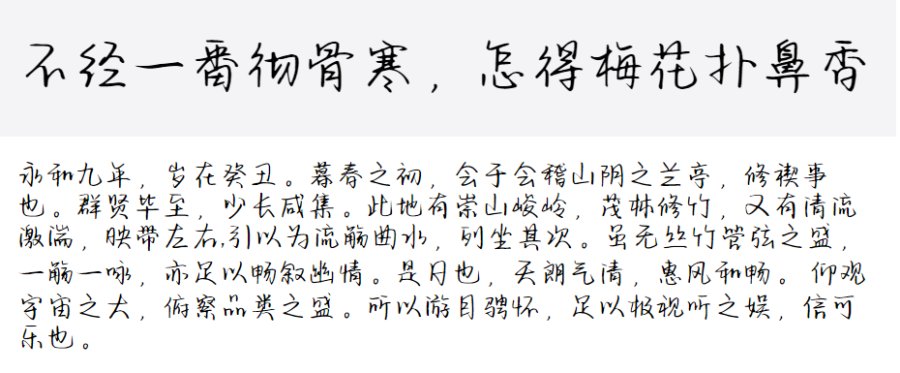
2、字语素笺体
字语素笺体这款字体笔画质朴,结构简单个性,转折处方中带圆,趣味十足。适用于动漫用字、少儿类书刊、品牌广告和产品包装设计,以及社交网络的个性化用字。
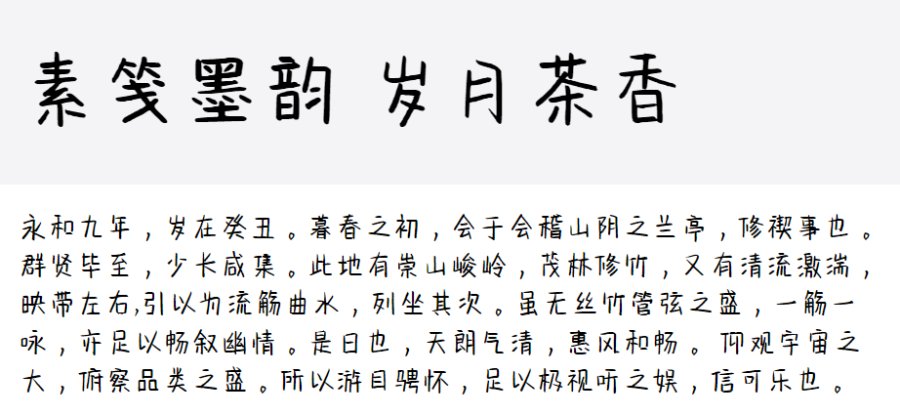
3、上首迎风手写体
上首迎风手写体,简体中文约6763字,字体笔画潇洒,从容凸显个性,给人极度轻松舒适感,适用于搭配标志、广告标语、商业广告等高端属性。
4、满船清梦压星河
满船清梦压星河这款字体的字骨骼清秀、遒劲有力。其个性优雅从容,适用于现代诗歌、短文的排版,以及文化、商业类品牌的广告语设计。
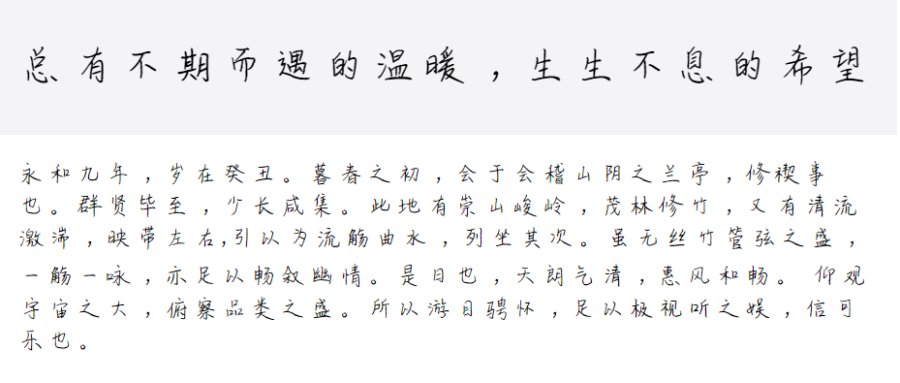
5、奶酪陷阱体
“奶酪陷阱体”,原型设计理念来自一块奶酪上雕刻的字体。字非常可爱,笔画弯曲有度,非常受广大年轻人喜欢。